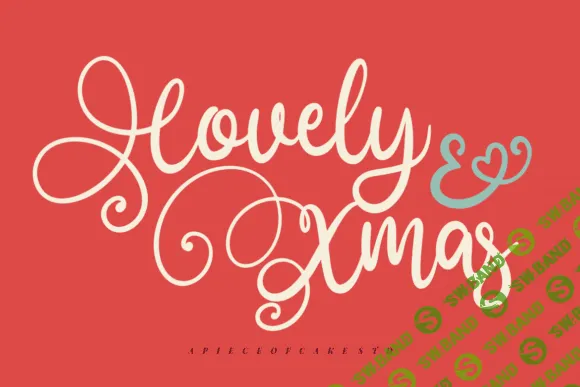
Название: Lovely Xmas Font (2021)
Lovely Xmas - это стильный и нежный рукописный шрифт.
Этот универсальный шрифт имеет широкий спектр применения - от поздравительных открыток до заголовков - и гарантированно придаст романтический настрой вашему следующему проекту.